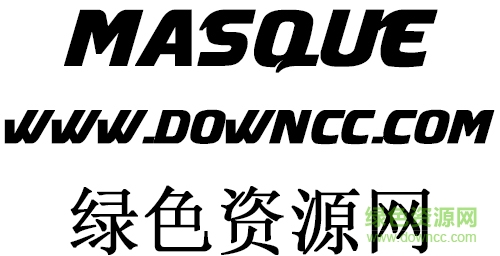
masque是一款非常有特色的英文字體,這款字體畫面粗壯、字形偏斜體,整體效果非常出色,可以廣泛應(yīng)用于廣告設(shè)計、排版印刷等領(lǐng)域,需要的朋友歡迎來綠色資源網(wǎng)下載體驗!
1.字體結(jié)構(gòu)合理,筆劃前后統(tǒng)一;
2.筆形剛健有力,個性豪放,視覺沖擊力強(qiáng);
3.適用于布置櫥窗、裝潢商品、制作廣告、設(shè)計書刊等;